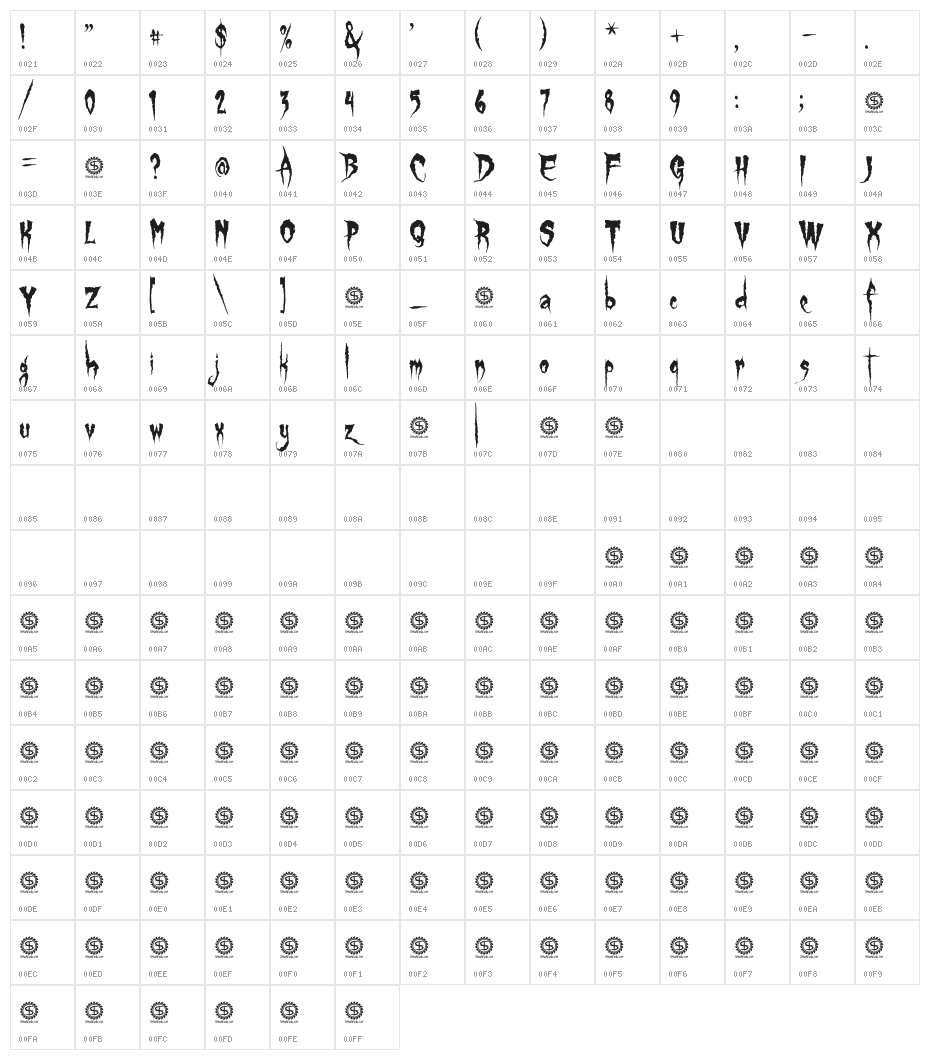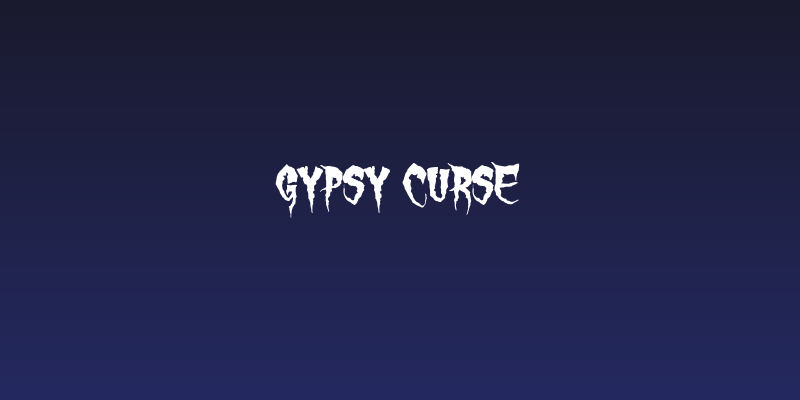
Gypsy Curse Font
✎ Horror
| Caso d'uso | Headlines, Posters, Themed Events |
| Progetti proposti | Ideal for Halloween-themed designs, horror movie posters, spooky invitations, or any project requiring a mysterious and unsettling vibe. |